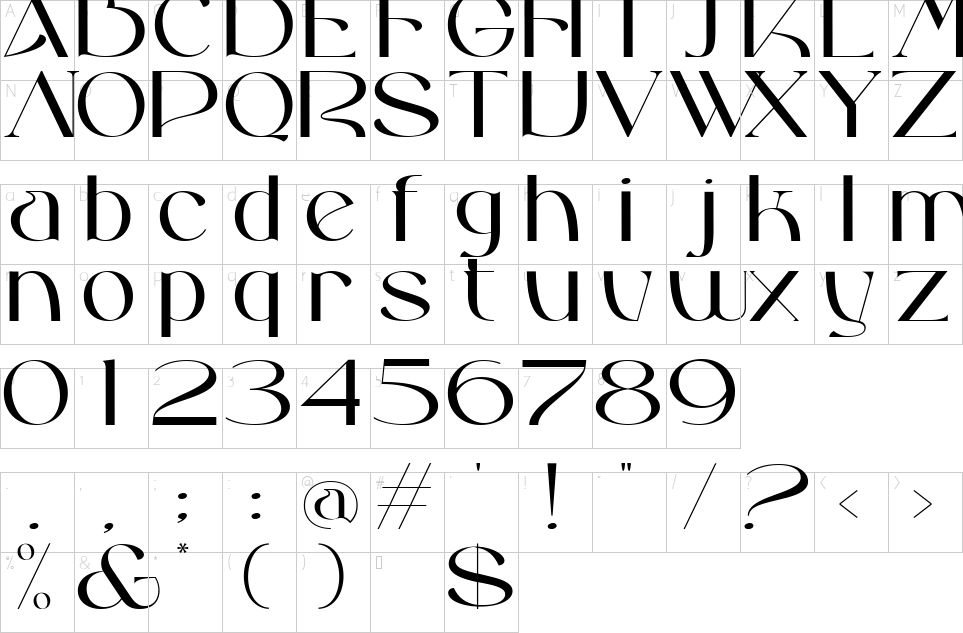
Descubra a elegância e a modernidade da fonte Masko. Desenvolvida pelo designer Areatype, Masko é uma opção incrível para quem procura uma fonte grata para seu próximo projeto. Esta fonte oferece um equilíbrio perfeito entre simplicidade e sofisticação, adequada para qualquer aplicação, desde logotipos até escrita no blog. Com um download total de 1.180 vezes, não há dúvida de que essa fonte é bem recebida no mundo dos designers. Instale a Masko e experimente a riqueza de detalhes que essa fonte tem a oferecer.